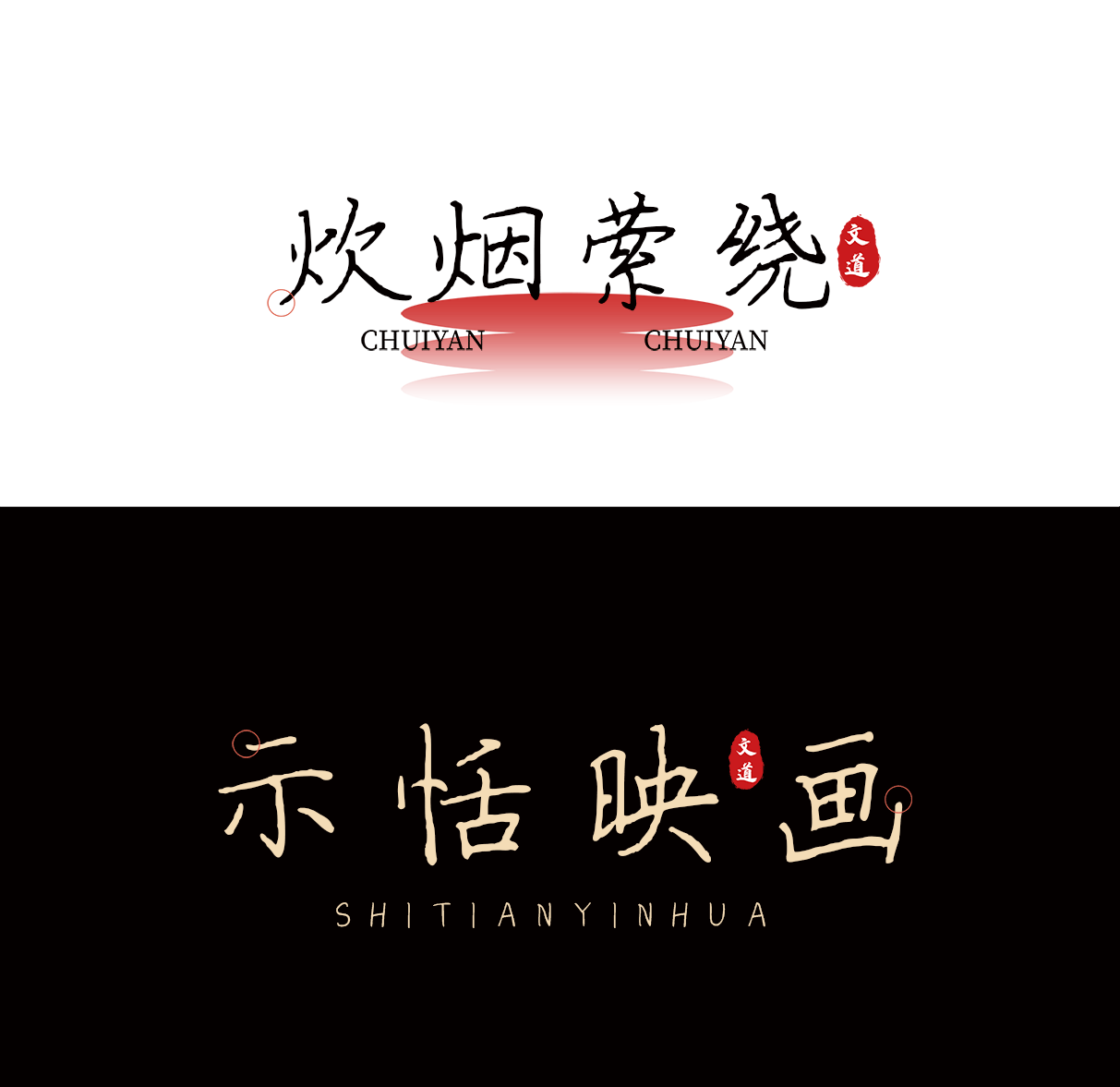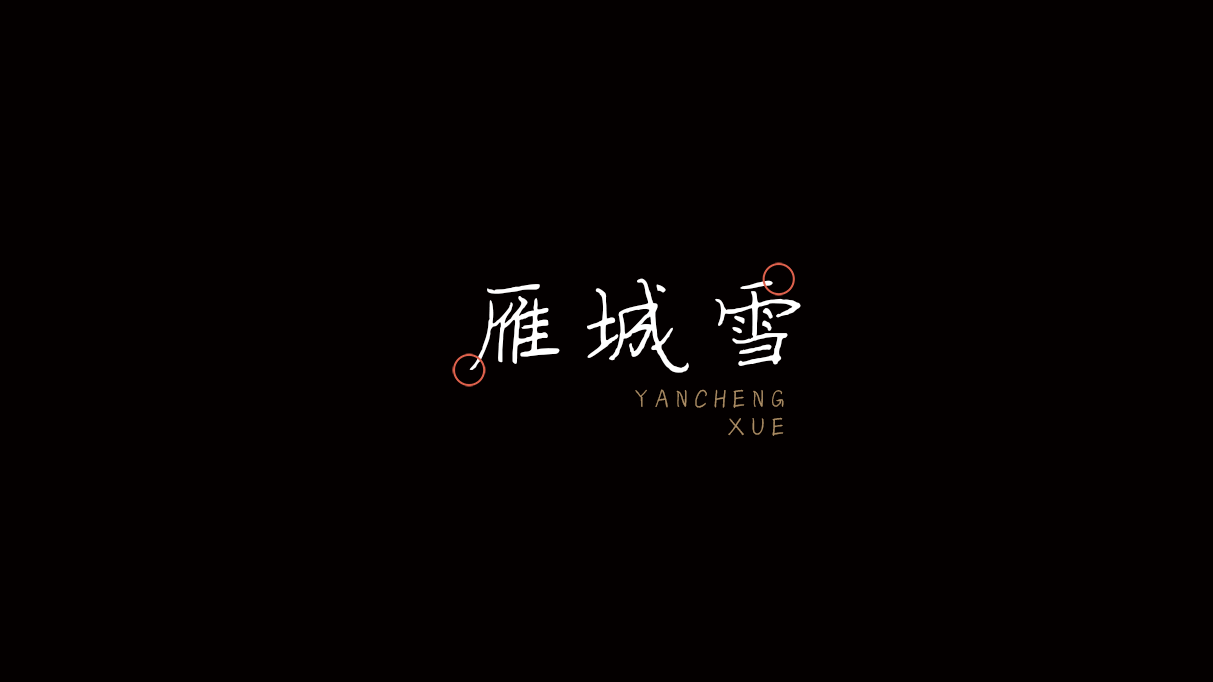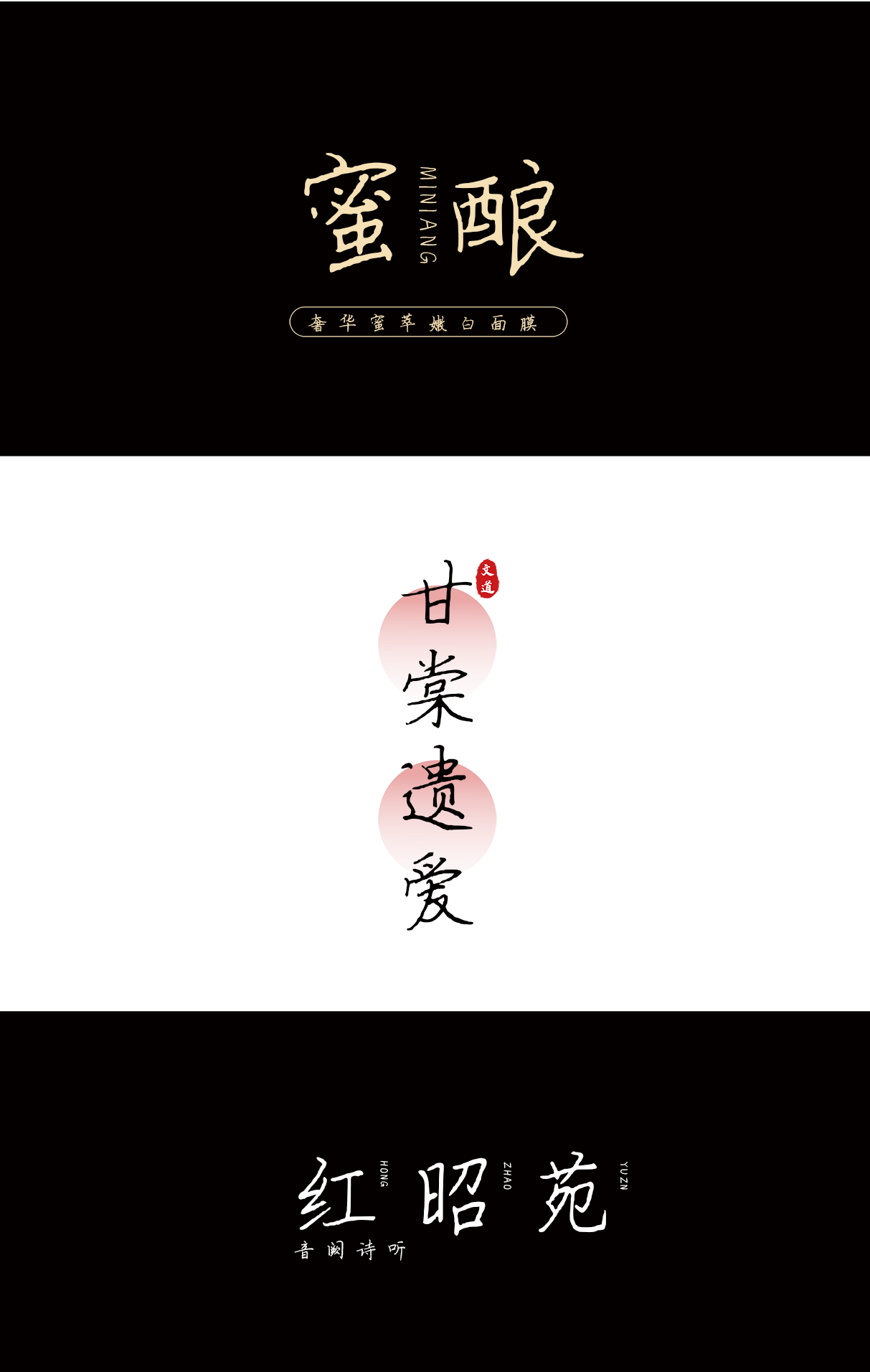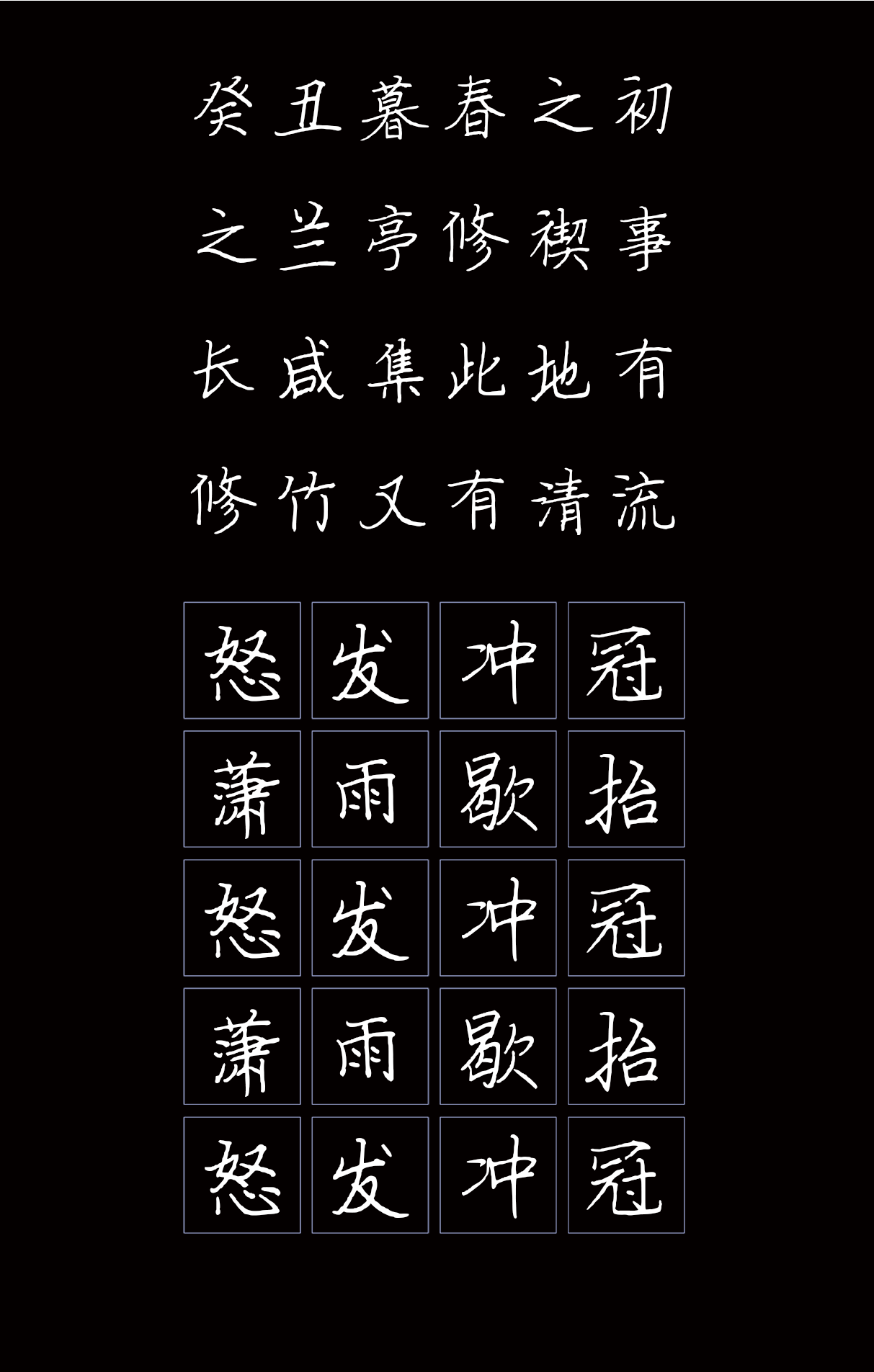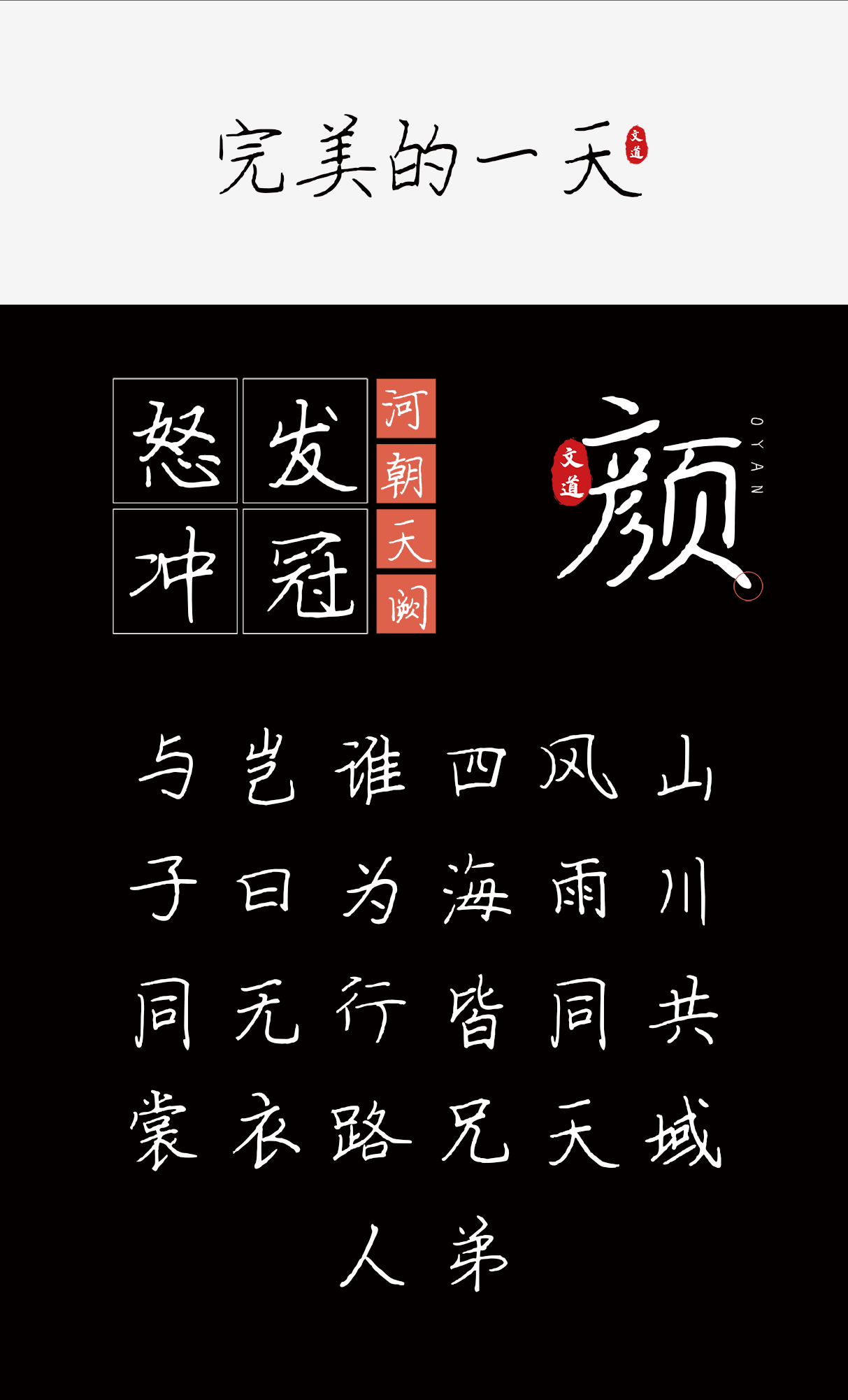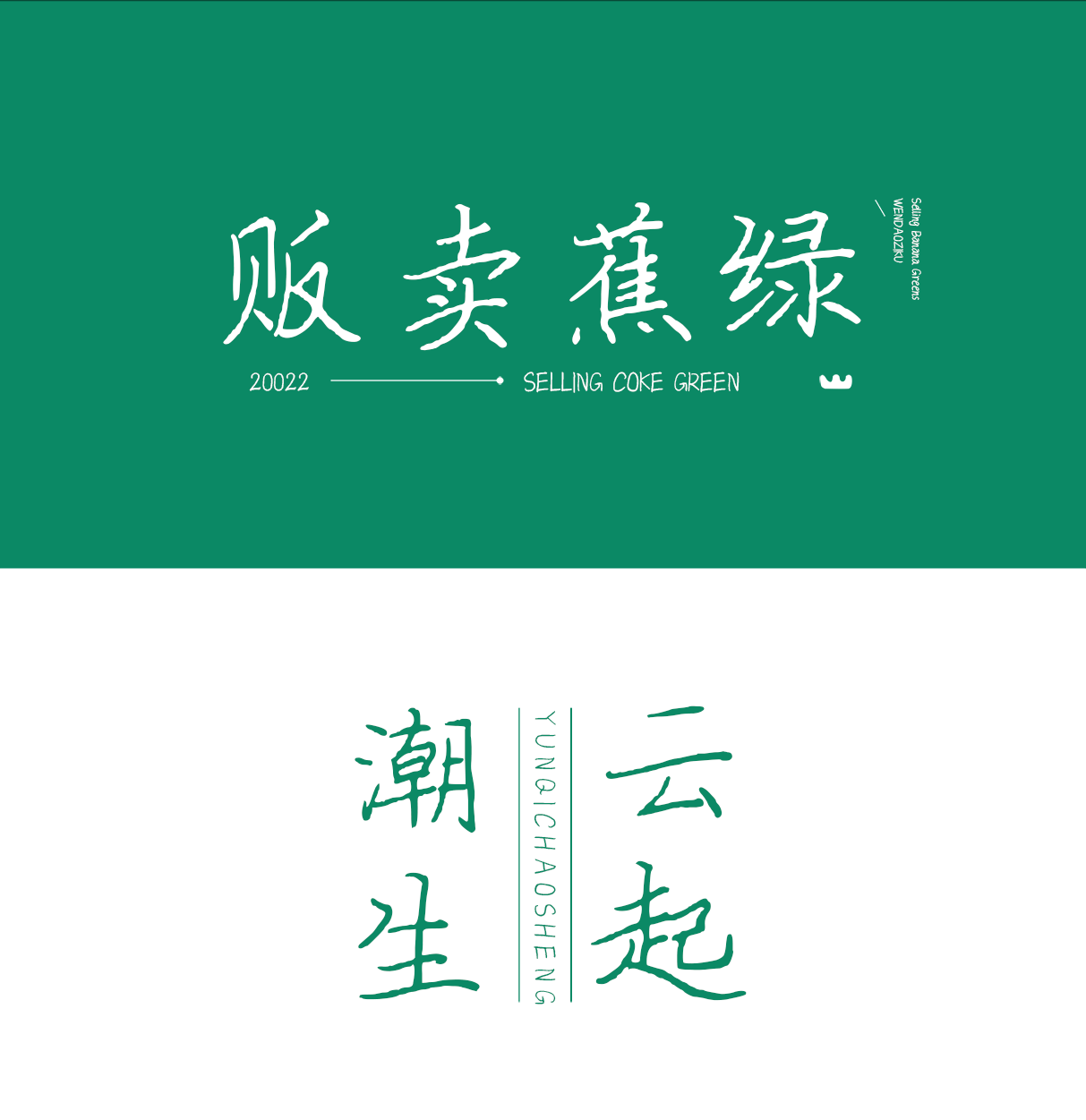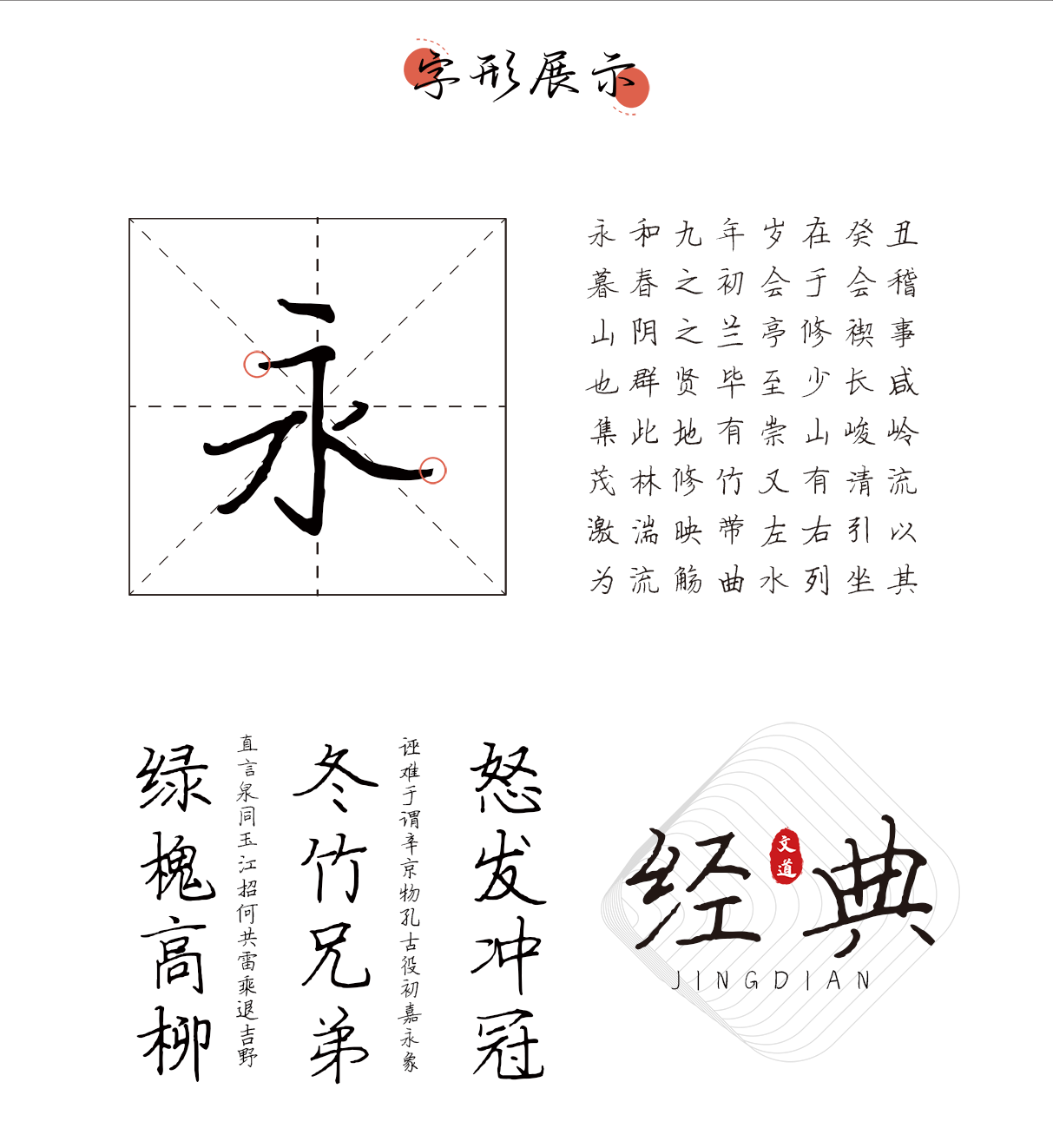
雁城雪
文亦有道,笔墨添香;墨韵飞扬,意蕴绵长。
字体名称: 雁城雪
适用场景: 游戏 电商 新媒 综艺 影视 海报
简介: 雁城雪字体介于楷隶之间,用笔震颤,笔形或若虬曲的树根,或若巍峨的峭壁。这款字体的风格苍劲朴拙,雄浑老辣,适用于传统食品、酒类品牌的广告和产品包装设计,以及影视、动漫和游戏的标题用字。